今回のバンドルは「厳選!人気の筆記体フォントセレクション」。いくつでも欲しい欧文スクリプトフォントが勢揃いしました。キュートな書体からストリート風のラフなものまで、様々な印象の筆記体フォントが楽しめるお得なコレクションが日本サイト限定販売中です。
「厳選!人気の筆記体フォントセレクション」の気になる中身は?
夏にぴったりのラフなイメージが魅力のSVGフォント:AVALLON
無料ではあまり商用可能なものに出会えないSVGフォントも、バンドルならお得なプライスで手に入れられます。「AVALLON」は写真やイラストと重ねることで、かすれたテクスチャを活かしたデザインが出来ますよ。
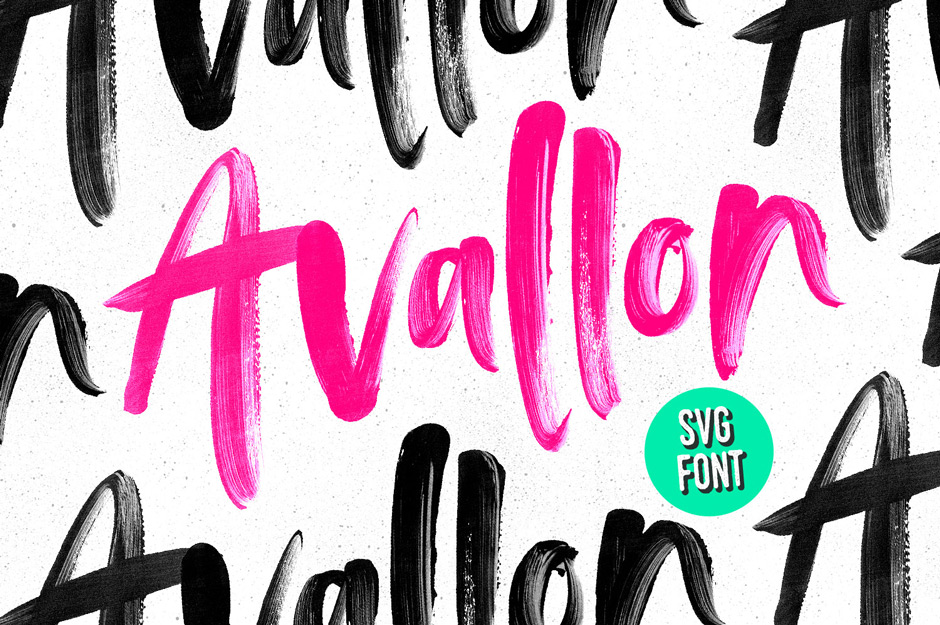
イラスト&ロゴテンプレートつきのかわいいスクリプトフォント:BUTTERMILK FARMHOUSE SCRIPT
かわいい雰囲気のスクリプトフォント「BUTTERMILK FARMHOUSE SCRIPT」は一緒に使えるイラストとロゴテンプレートも豊富に収録。あれこれ探す手間なく、カントリー風のロゴがすぐに作れます。
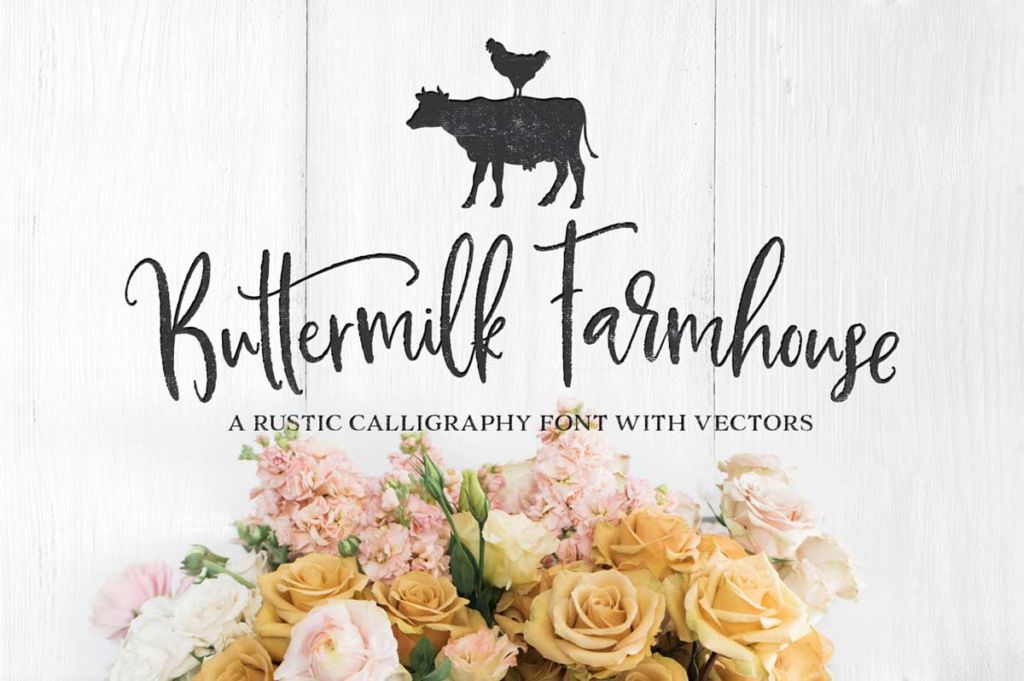
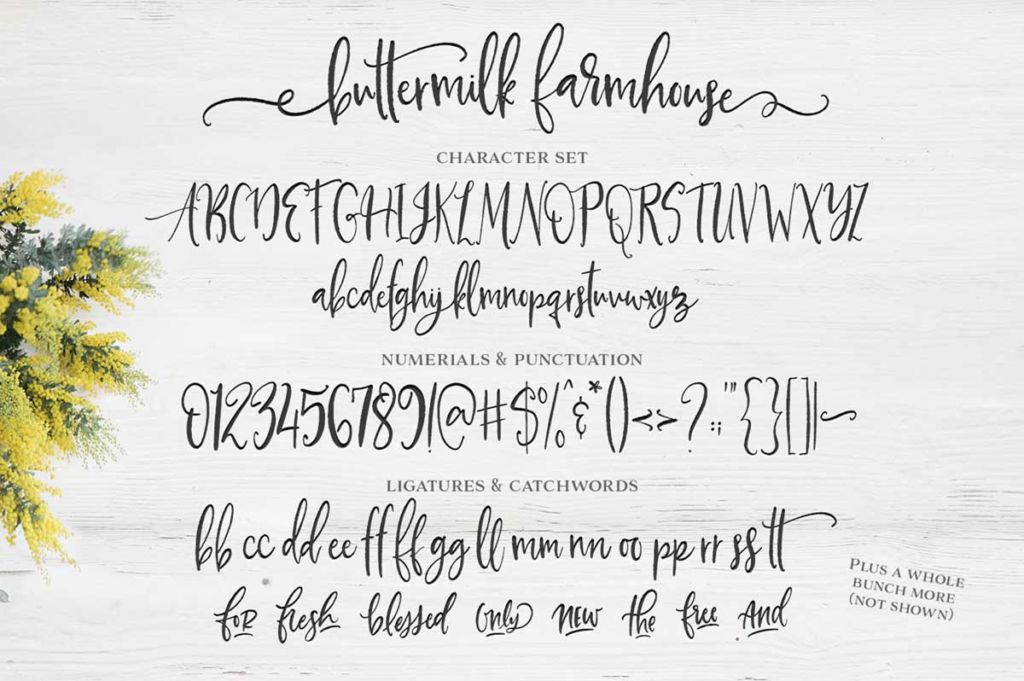
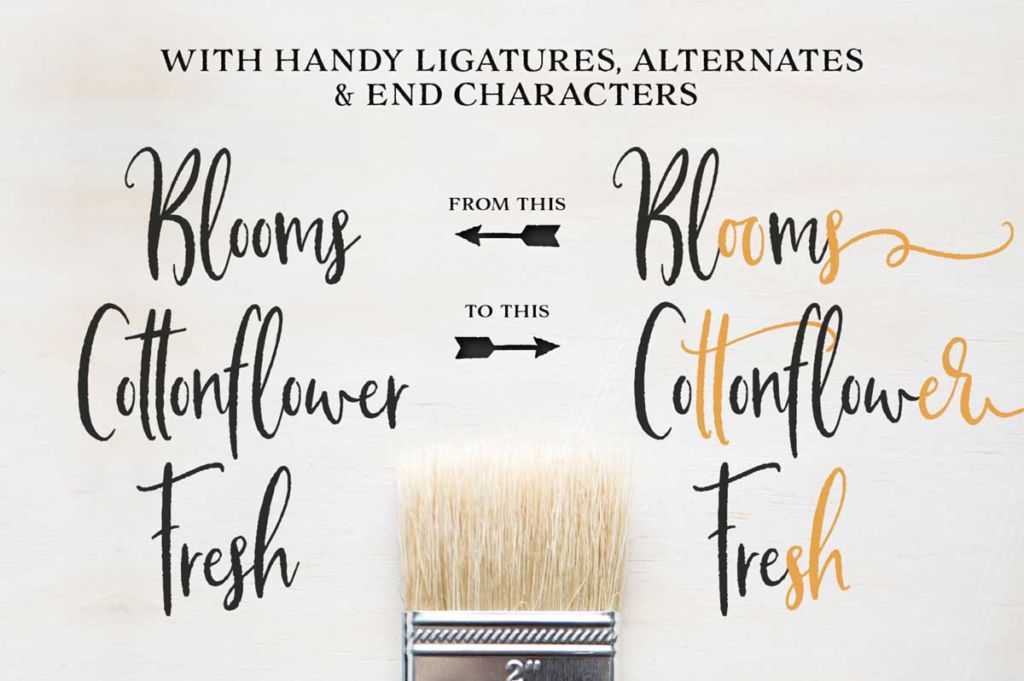
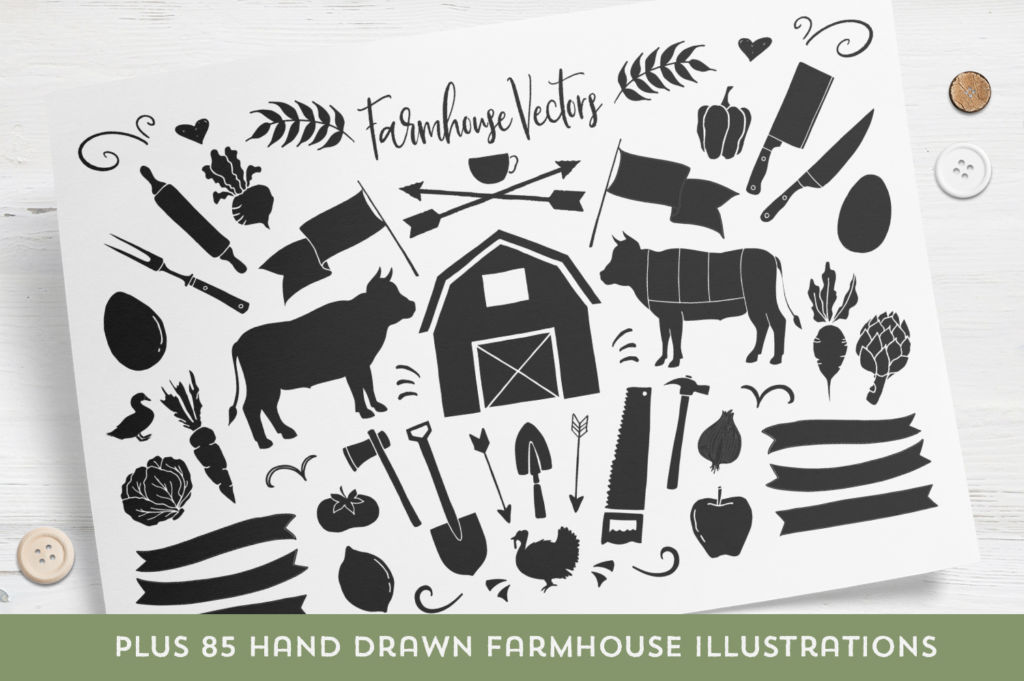
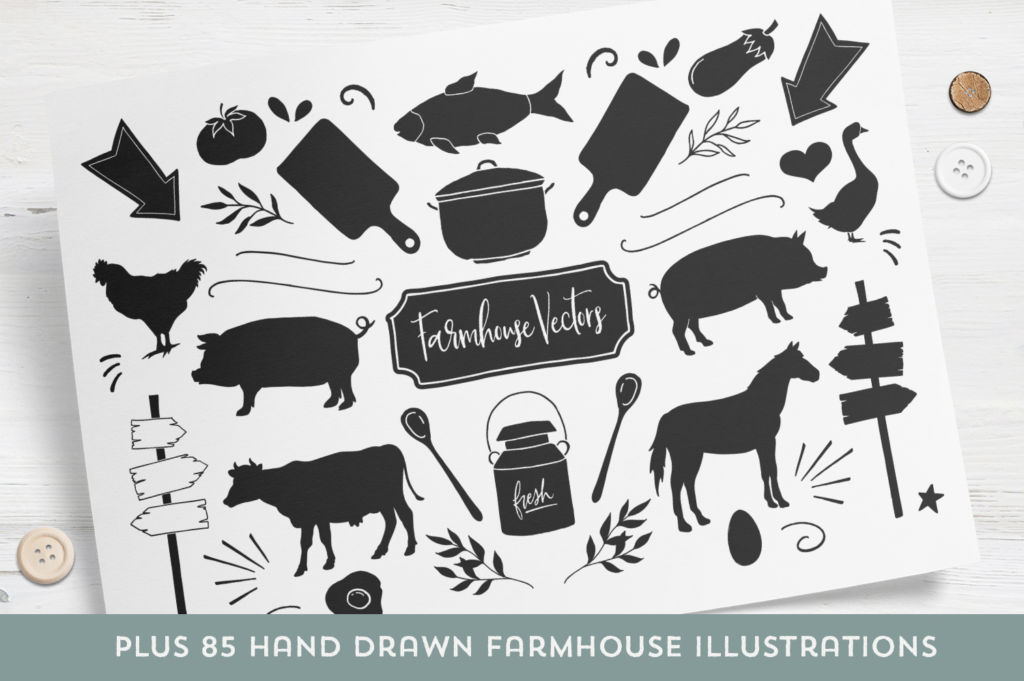
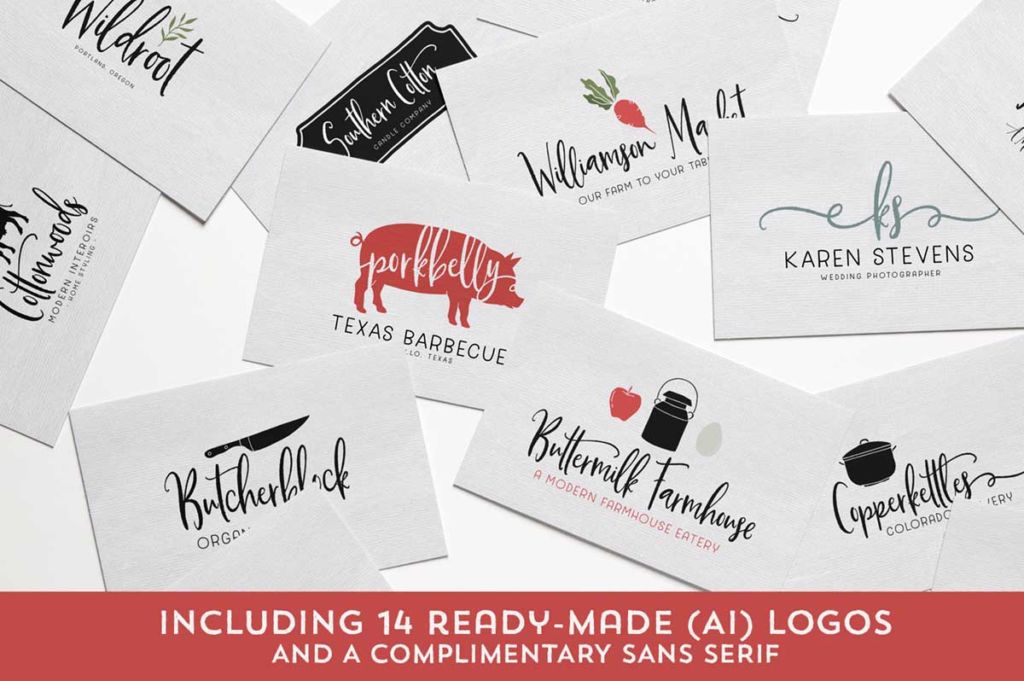
組み合わせに迷わず使えるフォントファミリー:ABOVE THE SKY FONT FAMILY
いつもフォントのペアリングに頭を悩ませている方にオススメの「ABOVE THE SKY FONT FAMILY」。ブラシ風4書体とマーカー風1書体のファミリーで、フォントの組み合わせに迷わずデザイン出来ます。
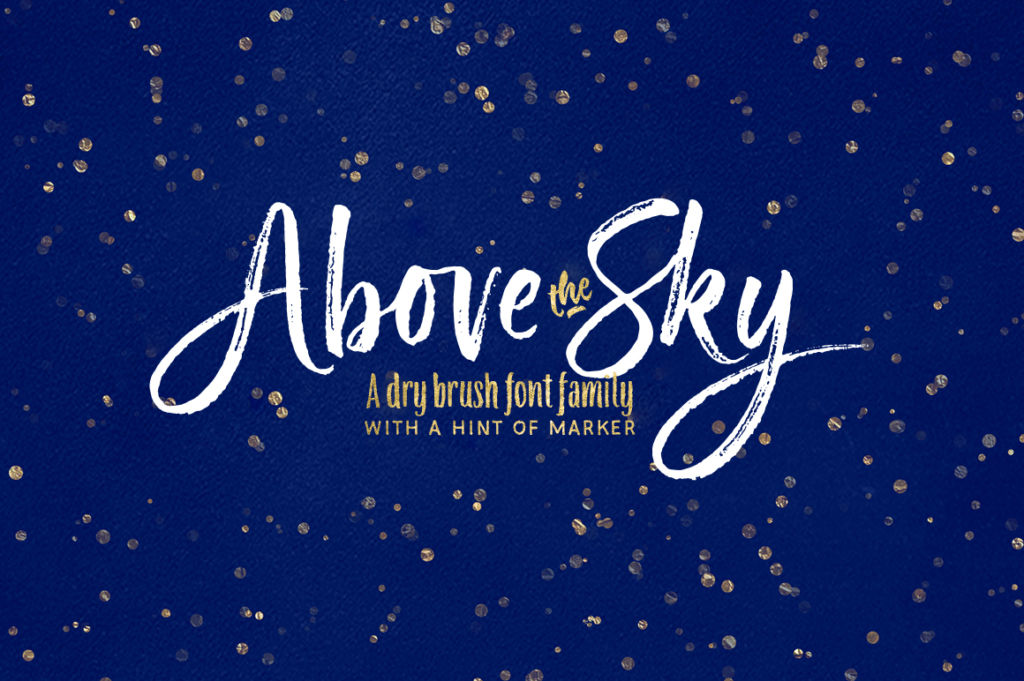
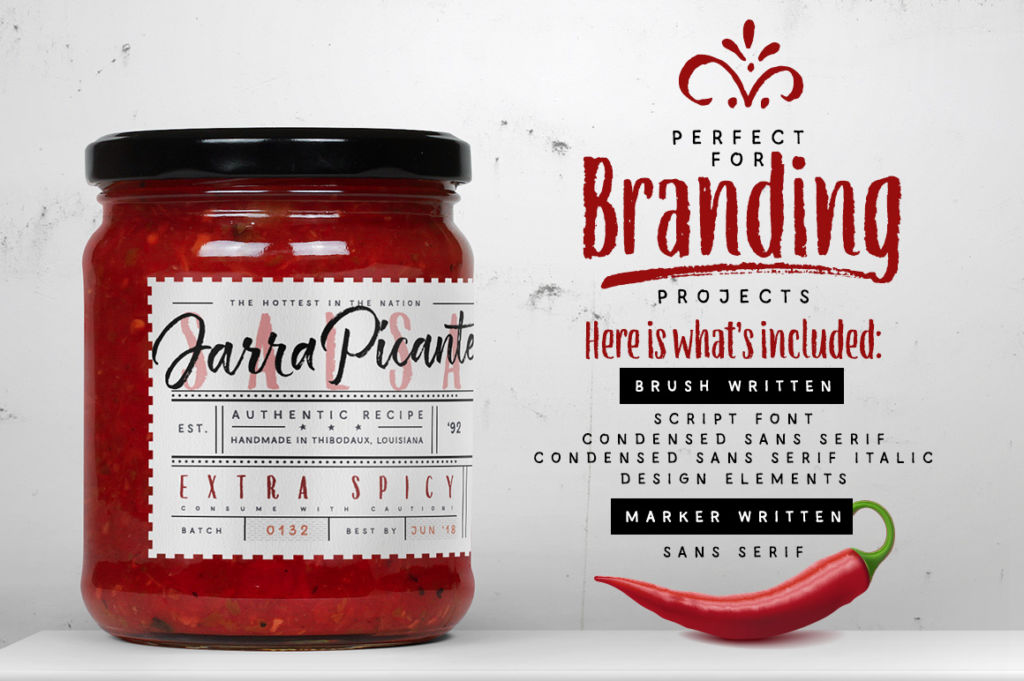
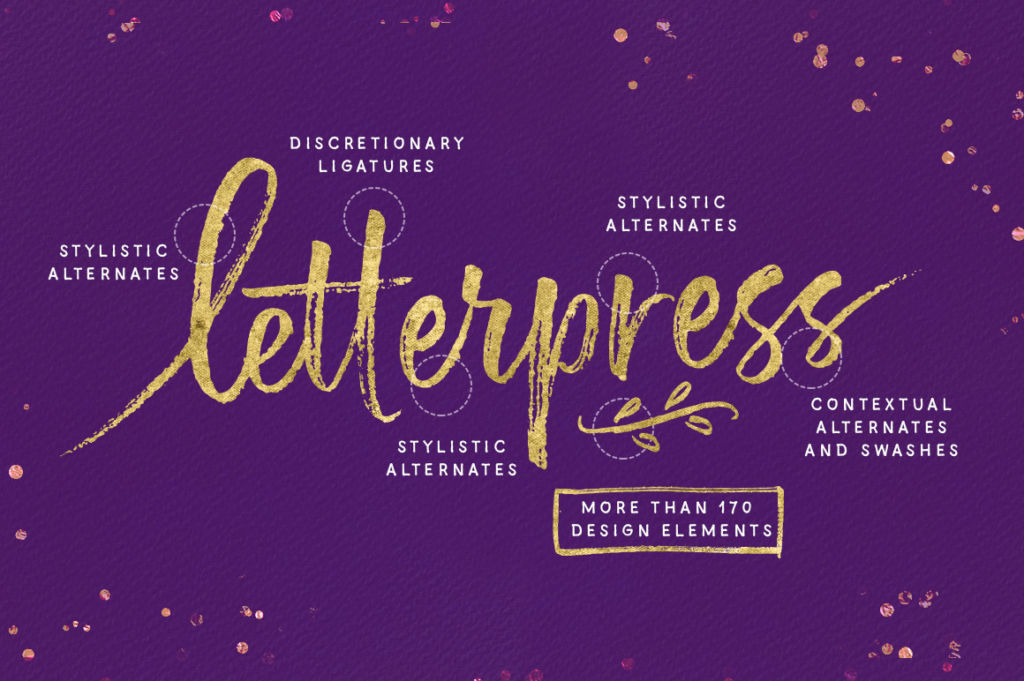
クリーンなスクリプト&セリフフォント:ABSOLUTE BEAUTY FONT FAMILY
繊細なセリフフォントと細ペンで書いたようなスクリプトフォントがセットになった「ABSOLUTE BEAUTY FONT FAMILY」。リガチャ(合字)も数パターン用意されていて、どんなスペルでも美しくデザインできます。
レトロな雰囲気のスクリプトフォントセット:GOLD COAST – VINTAGE SERIF + EXTRAS
3種類のスタイルが選べる、レトロ風なスクリプトフォント「GOLD COAST – VINTAGE SERIF + EXTRAS」。嬉しいロゴテンプレートつきです。